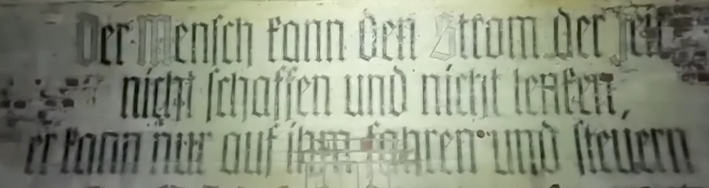
ich habe so einige Zeit für das Suchen im Netz verbracht und komme einfach nicht drauf, um welche Schriftart es sich dabei handelt. Eine einfache oder reguläre Fraktur ist es nicht, wenn man verschiedene Frakturen vergleicht. Also ich steht an.
Das folgende Bild stammt aus einem Video, in dem alte Bunker gezeigt werden ( https://www.youtube.com/watch?v=RQhMuILXLwM)
Und nein, ich benötige keine Schriften/Fonts. Mich interessieren einfach allgemein alte Schriften und eine solche kann ich leider nicht zuteilen.